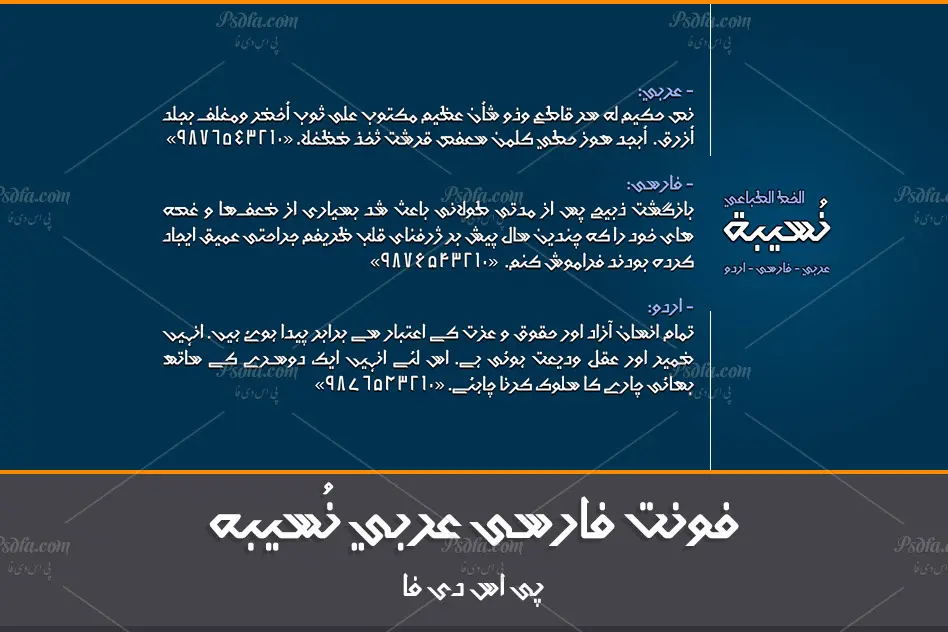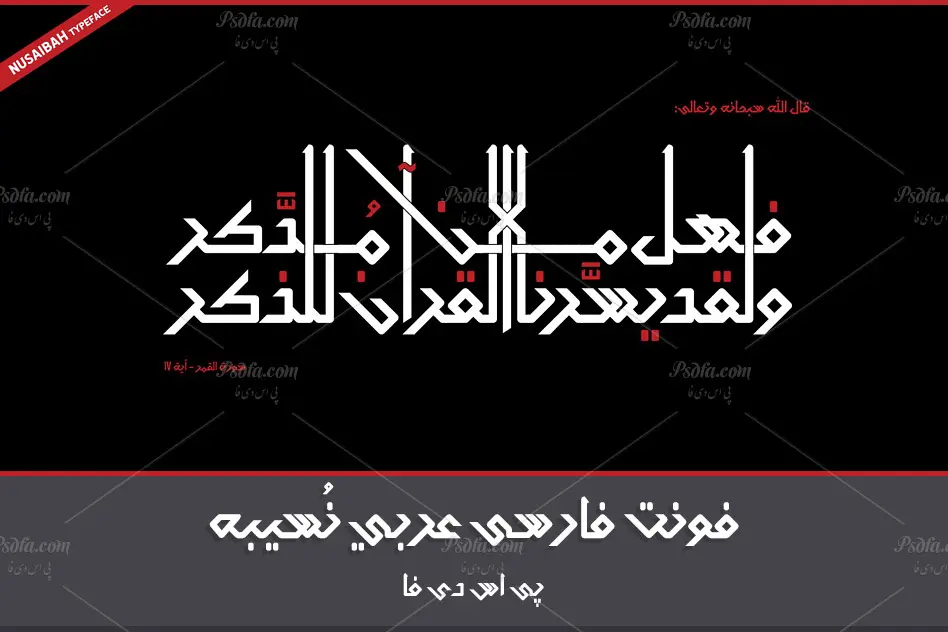
فونت عربی نسیبه مخصوص تایپوگرافی اسلیمی Nusaibah Arabic Font
فونت فارسی عربی نسیبه
در این مطلب شاهد فونت فارسی عربی نسیبه Nusaibah Arabic Font مخصوص تایپوگرافی و طرح های اسلیمی می باشید. این فونت زیبا در قالب 2 فایل otf و woff بر روی سایت بارگذاری شده اند که با نصب فرمت otf در پوشه فونت های سیستم قادر به استفاده از آن در تمام نرم افزارهای گرافیکی و ویرایشگر متن از جمله نرم افزار فتوشاپ ، پریمیر ، افترافکت ، مجموعه نرم افزار آفیس و … خواهید بود. فونت نسیبه در دو وزن معمولی (Regular) و ضخیم (Bold) طراحی شده است که می توان از آن در انواع طراحی به خصوص ایجاد تایپوگرافی ، طراحی پوستر ، تراکت ، بروشور ، بنر و … استفاده نمود. همچنین از فرمت woff این فونت می توان در طراحی صفحات وب نیز استفاده کرد.
- نام فونت : فونت فارسی عربی نُسیبه